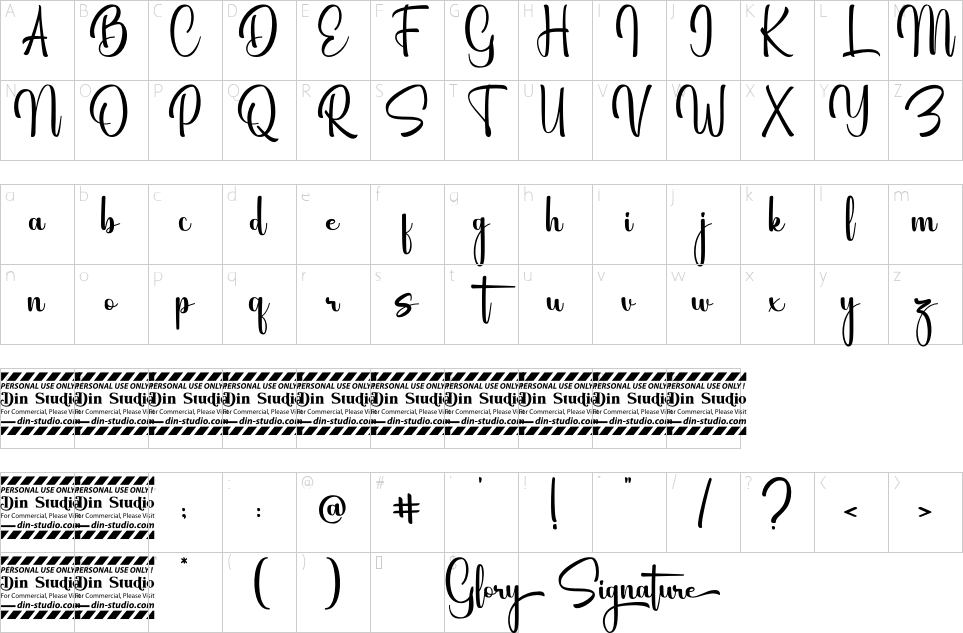
Glory Signature Font | 1001 Free Fonts – Download Grátis
A fonte ‘Glory Signature’ é uma elegante escolha para qualquer projeto de design, destacando-se entre as outras graças à sua personalidade única e fluida. Desenhada pela Din Studio, ela é uma fonte de estilo moderno que oferece uma textura sofisticada, perfeita para criar gráficos que chamem a atenção. Aproveite suas características fluidas para criar layouts de texto com um toque distintivo, ou experimente seus gráficos em aplicações de design de gráficos e editor de imagens. Com seu design cuidadosamente cuidado e seu formato de download rápido, ‘Glory Signature’ é uma excelente opção para quem procura um design de fonte atraente e fácil de usar. Com 5,253 downloads, é uma fonte de alta qualidade que você certamente vai querer ter no seu arsenal de recursos gráficos.